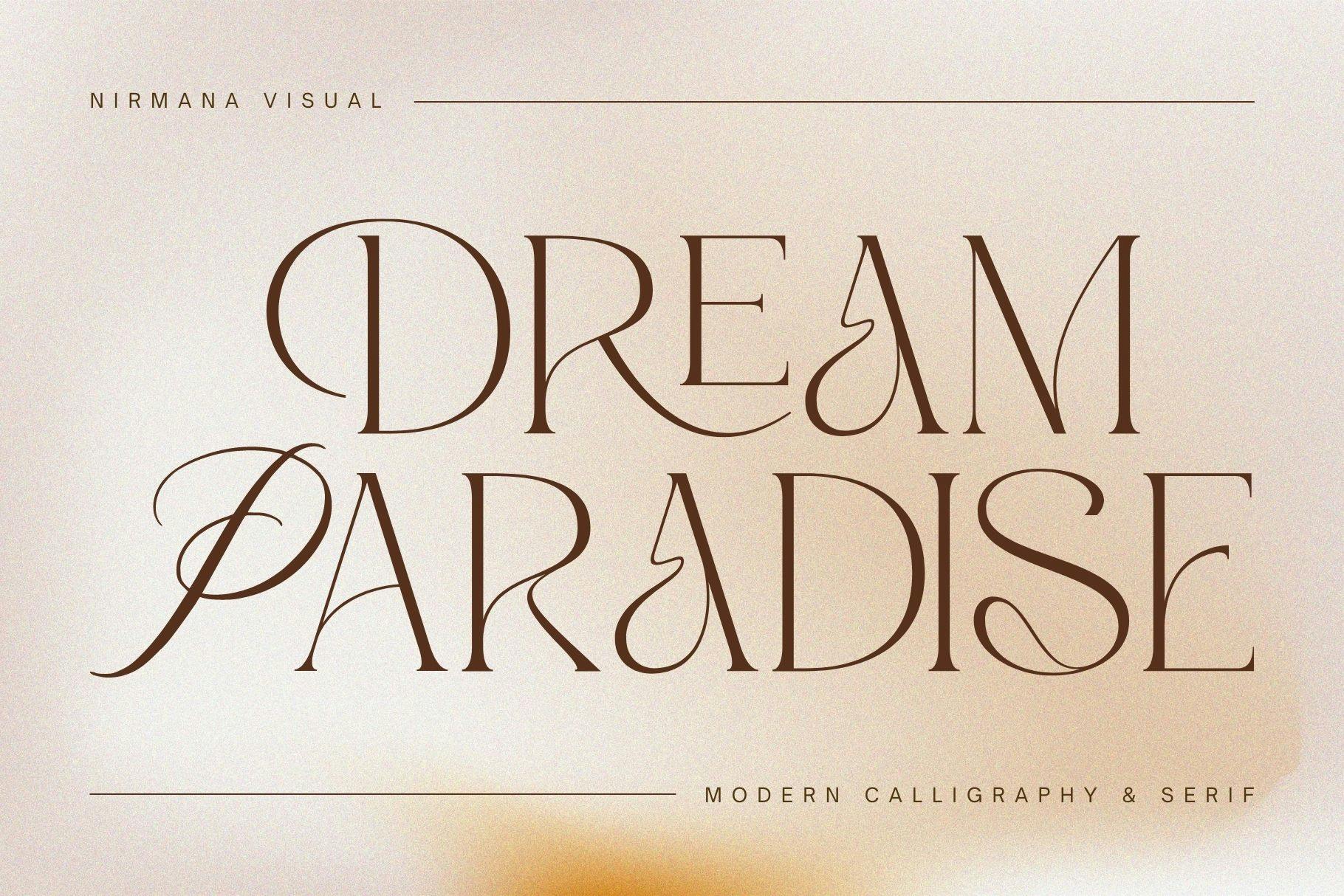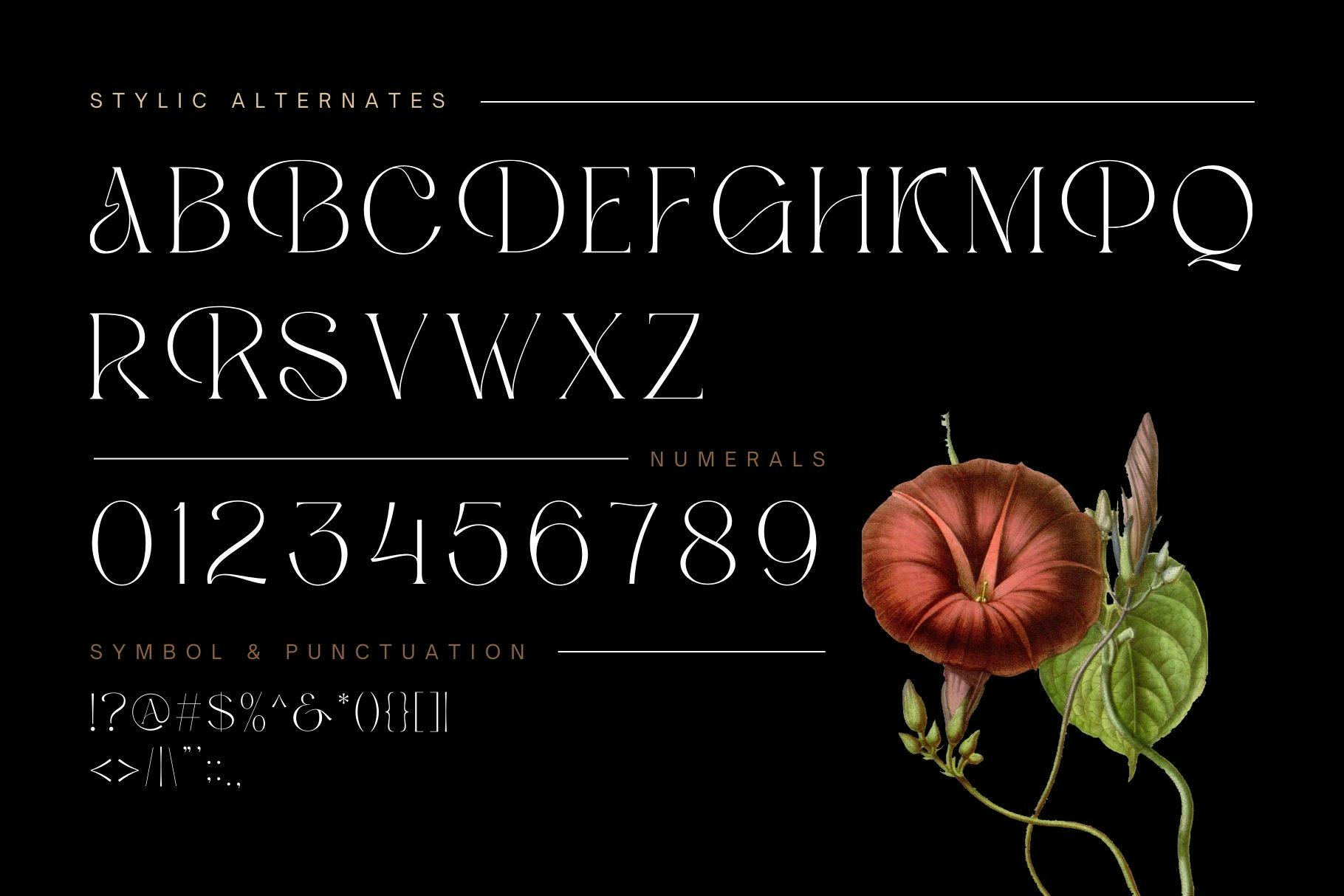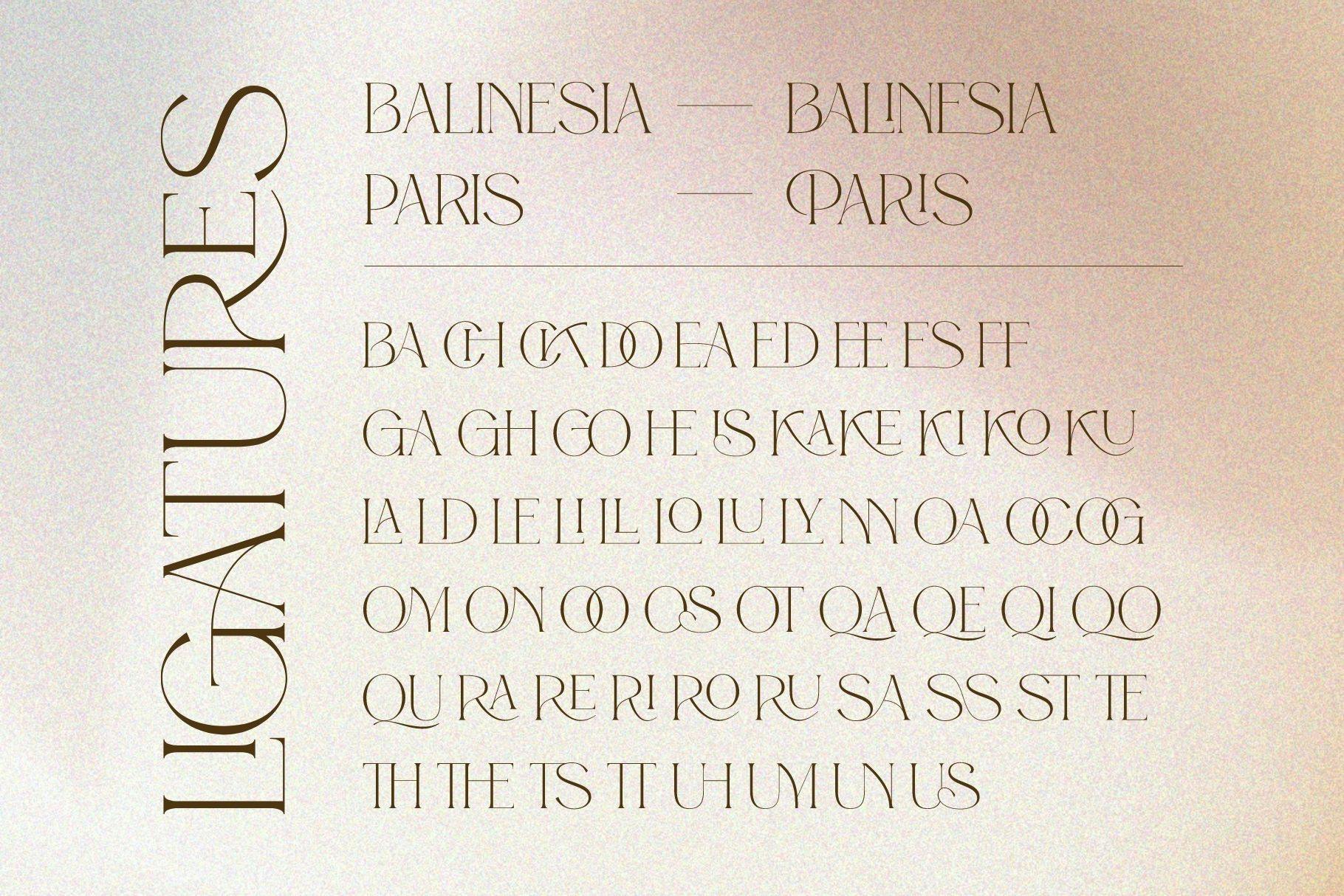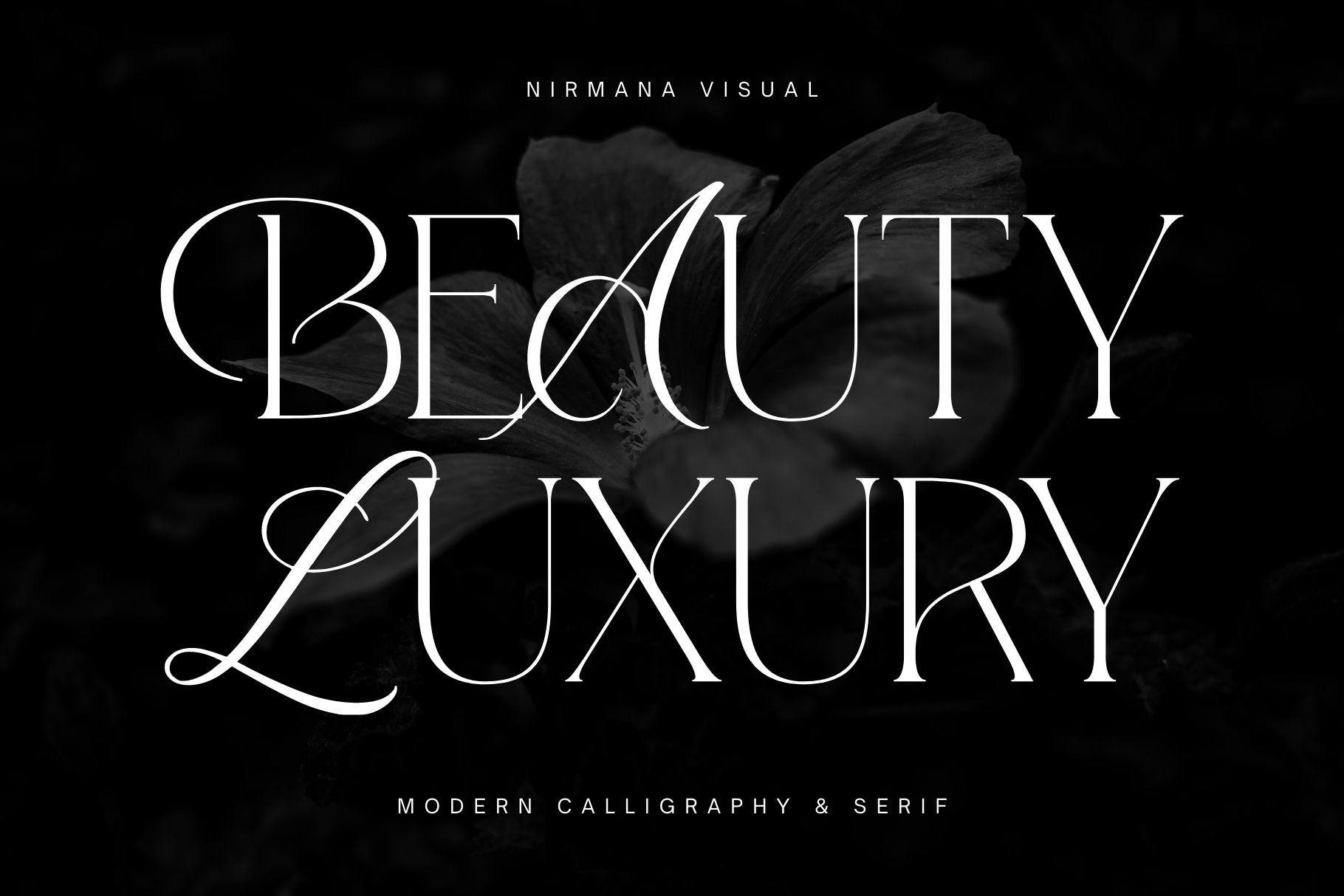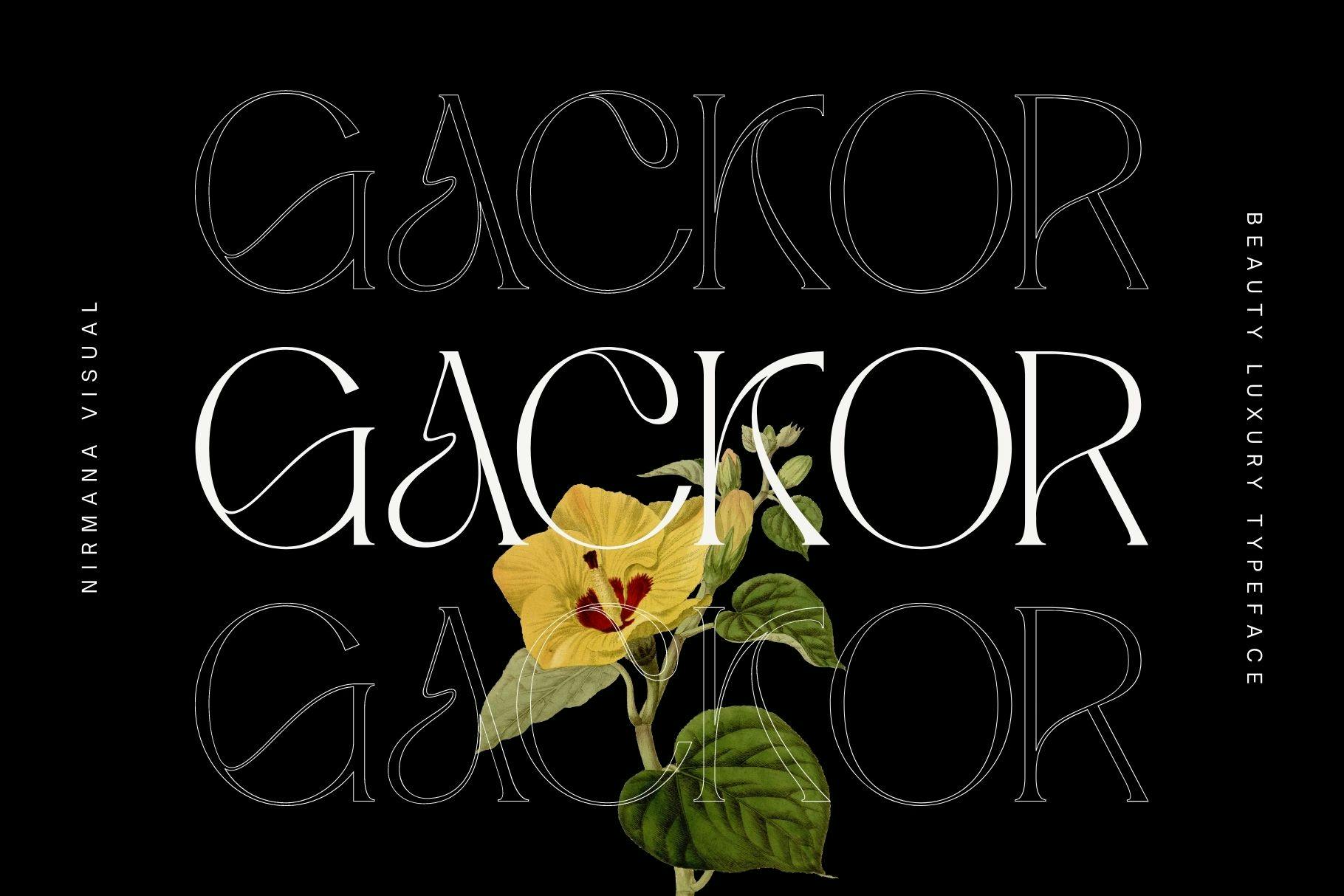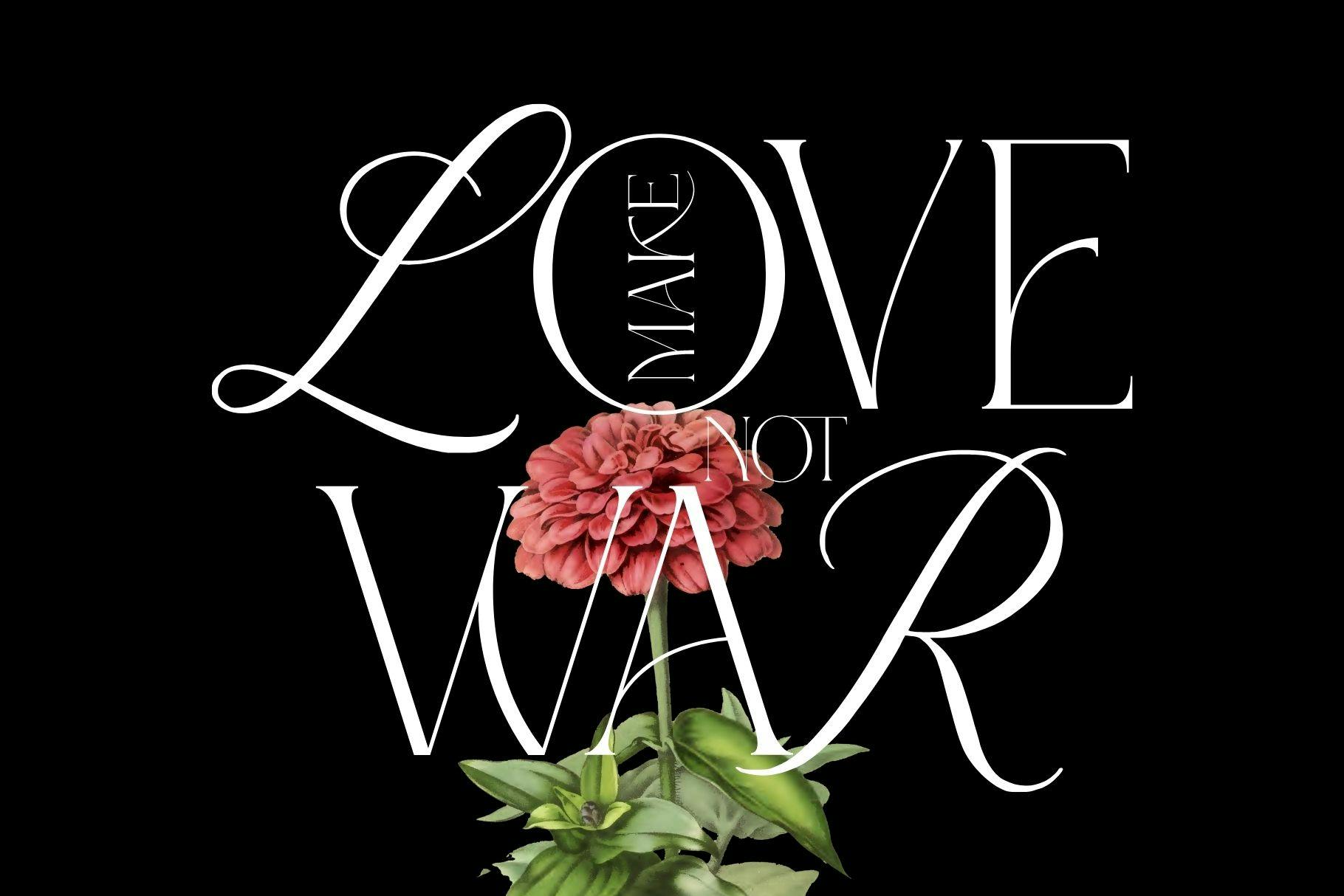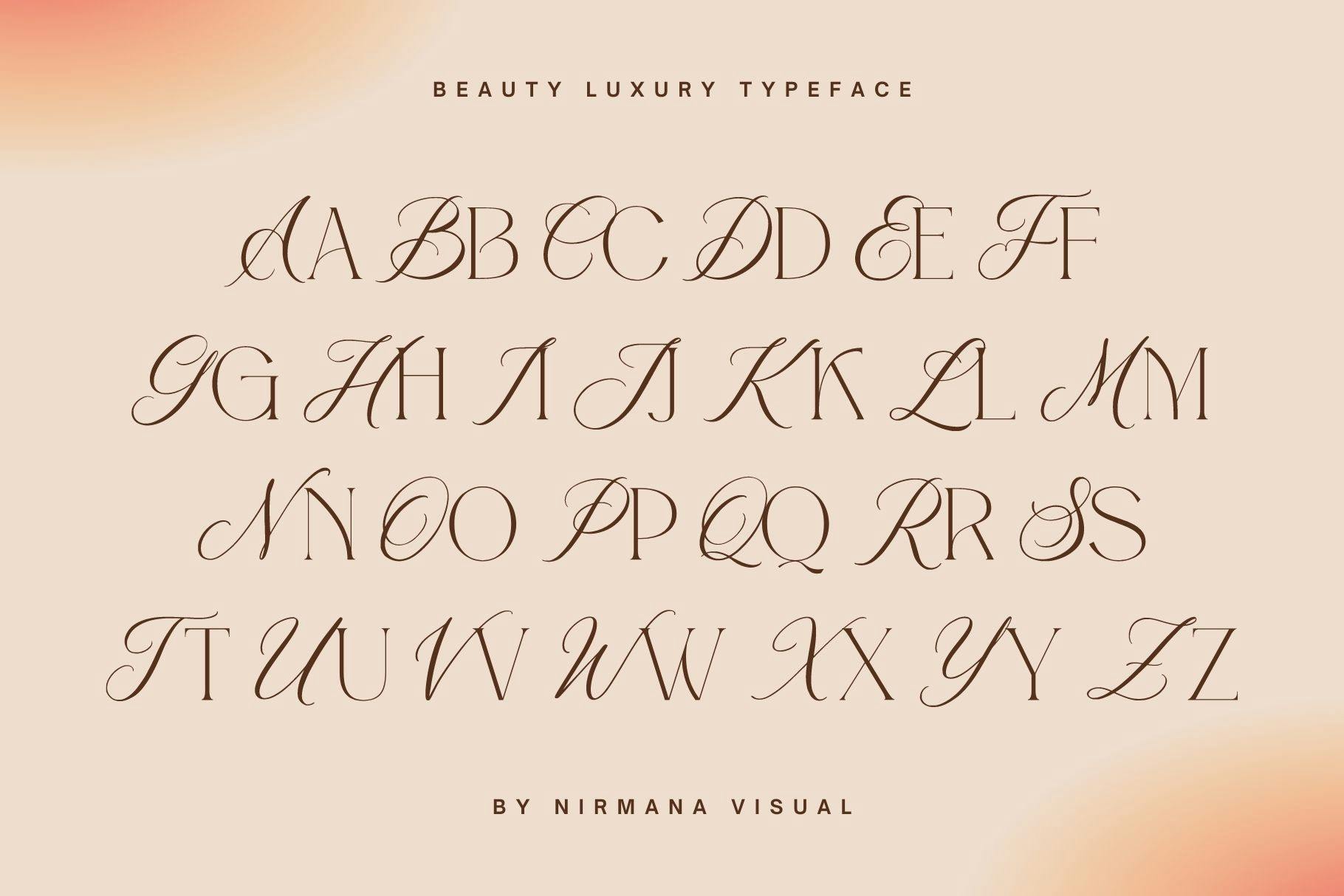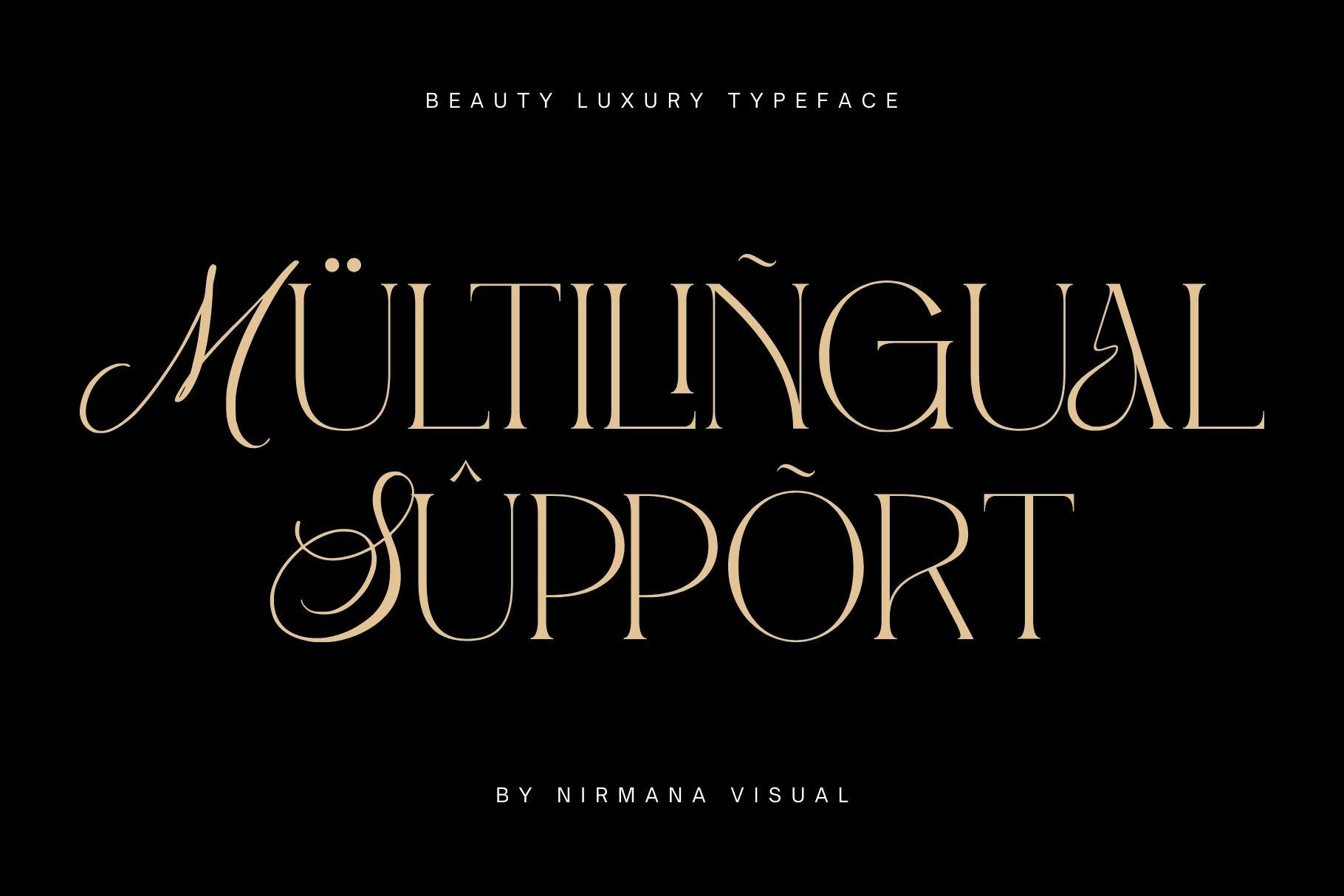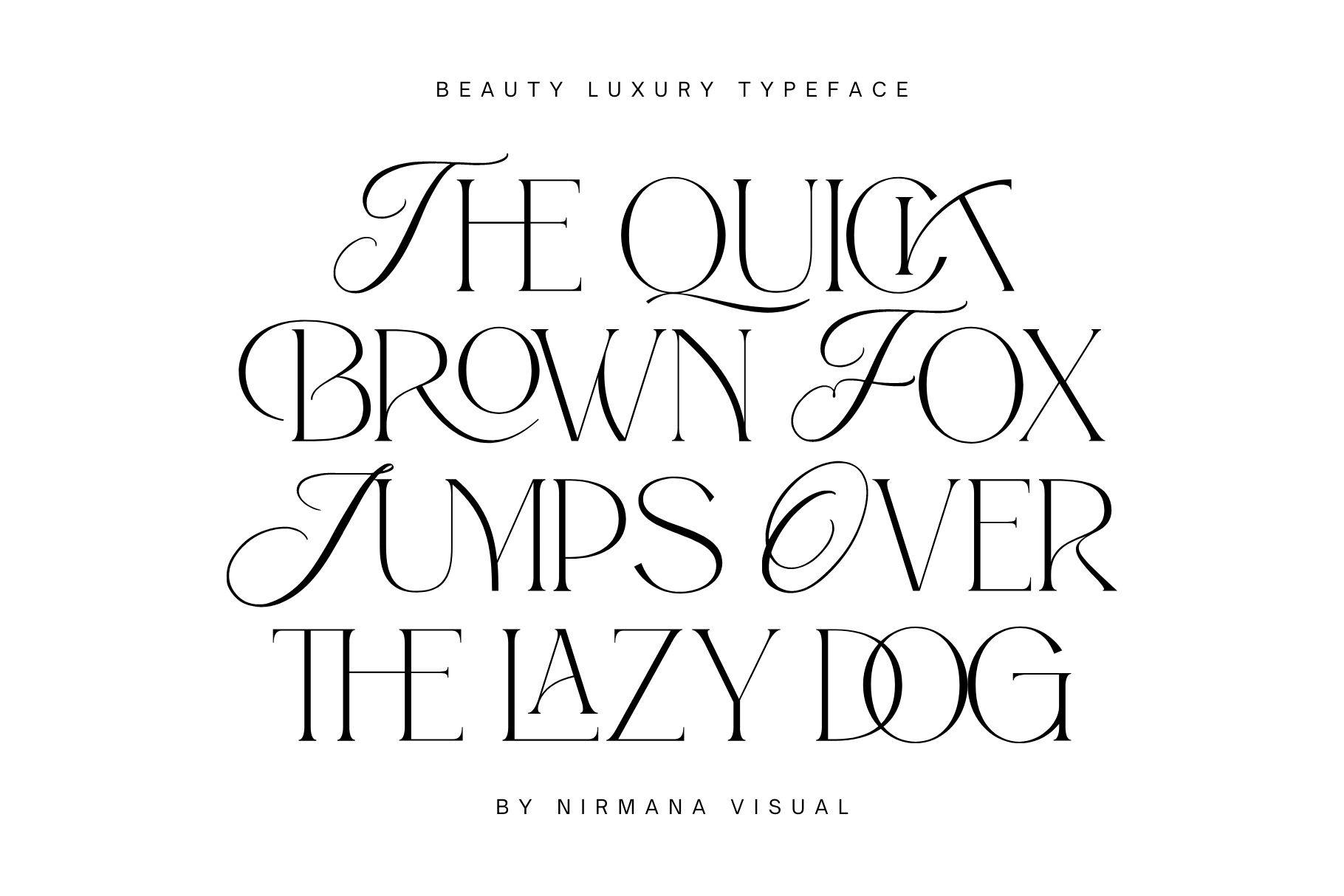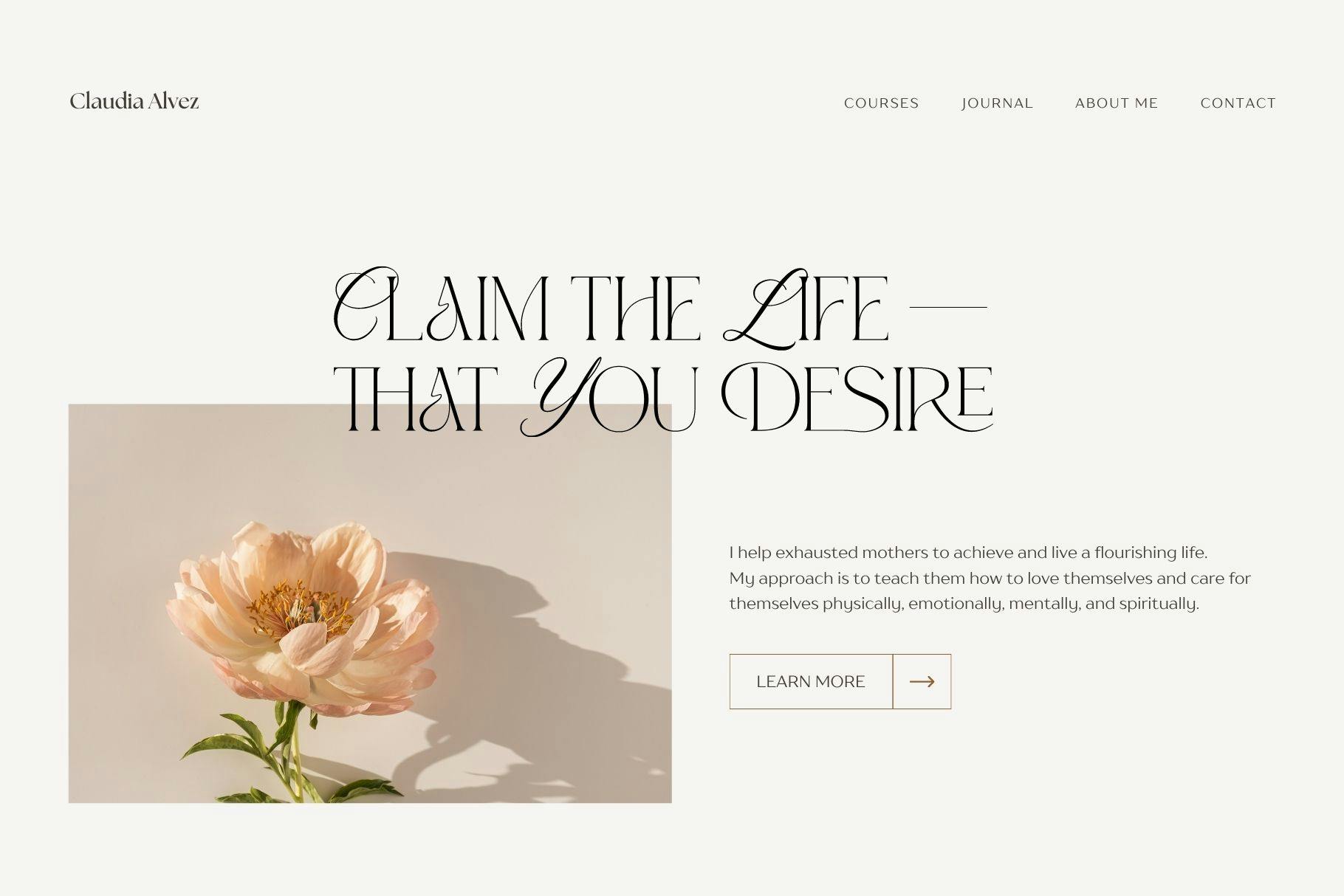
Beauty Luxury Logo Font
فونت Beauty Luxury با طراحی مدرن و شیک مناسب برای پروژه‌های شما.
Beauty Luxury یک فونت لوکس و زیبا است که ترکیبی از خوشنویسی مدرن و Serif می‌باشد. این فونت شامل مجموعه کاملی از حروف کوچک و بزرگ، اعداد و نشانه‌های نگارشی و نمادهای چند زبانه است.